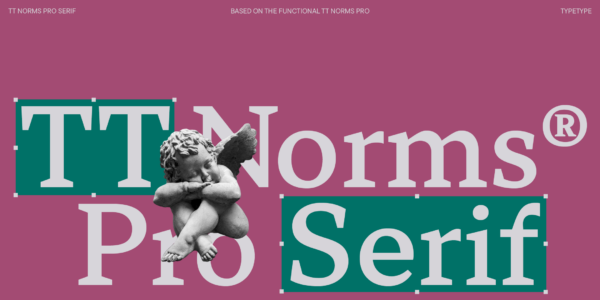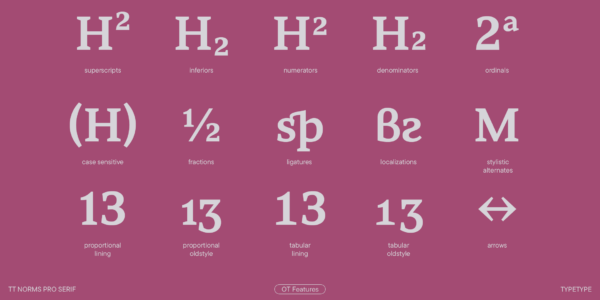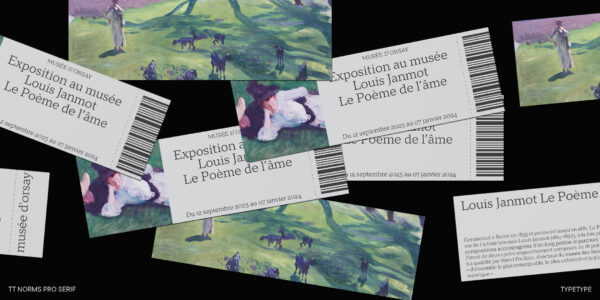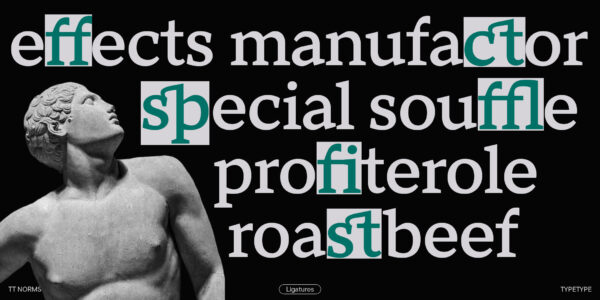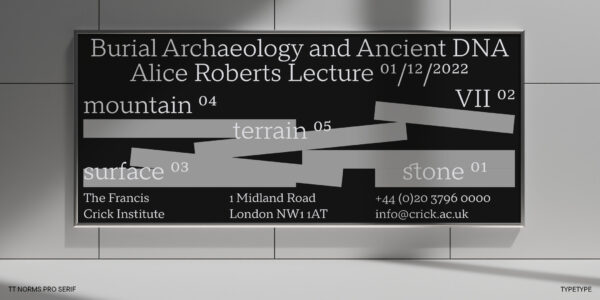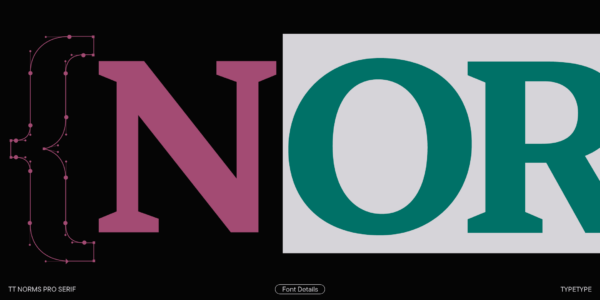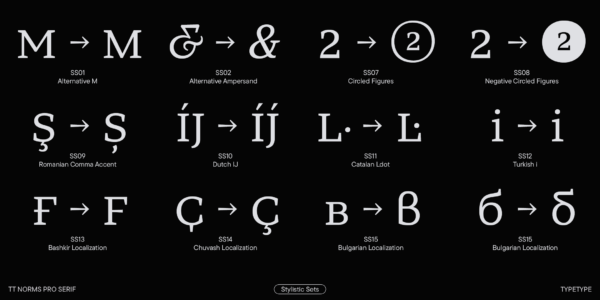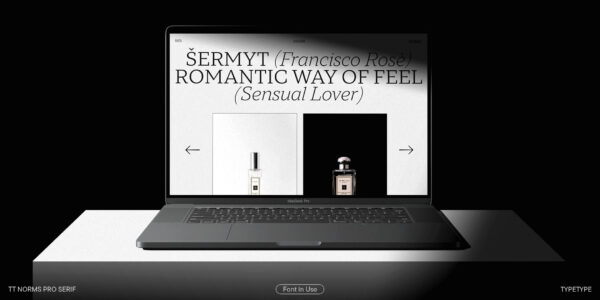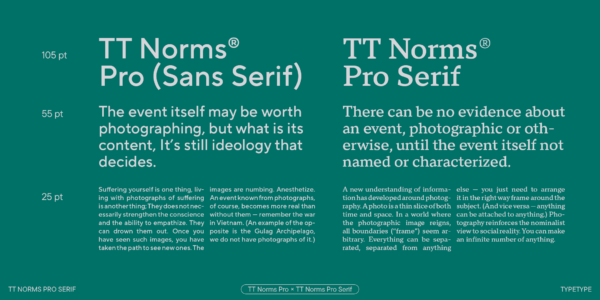
TT Norms® Pro Serif
TT Norms® Pro Serif — TT Нормс Про Сериф
«TT Norms» является зарегистрированным товарным знаком. «Pro» произносится как «про», и является разговорным сокращением слова профессиональный. «Serif» произносится как «сериф», в переводе с английского «антиква».
TT Norms® Pro Serif — функциональная и нейтральная, при этом элегантная антиква. Разработана на основе бестселлера TT Norms® Pro.
TT Norms Pro Serif — идеальная пара для главного гротеска от студии TypeType
В конце 2021 года мы задумали спроектировать антикву в пару к нашему бестселлеру TT Norms® Pro. Разработка шрифта заняла ровно один год. Данную антикву легко узнать по небольшому контрасту в пропорциях, наклону оси овалов, динамике ширин и контрасту в диагоналях. TT Norms Pro Serif — не просто дополнение, это полноценная антиква на базе функционального гротеска TT Norms® Pro. Наша новая антиква может использоваться на сайтах, для верстки книг, для оформления упаковок. В 2023 году мы провели большое обновление данного семейства, добавив несколько новых языков и опентайп фич.
1380 знаков, более 235 языков
Встречайте TT Norms® Pro Serif версии 1.100! Увеличили знаковый состав, добавили новые OpenType фичи и локализации для сербского и болгарского языков.
TT Norms® Pro Serif — функциональная антиква, разработанная на основе главного бестселлера студии — универсального гротеска TT Norms® Pro. Вместе они образуют идеальную шрифтовую пару. И хотя эти гарнитуры созданы друг для друга, они легко могут использоваться самостоятельно или составлять пару другим шрифтам.
Так, TT Norms® Pro Serif — самодостаточная, элегантная антиква, при этом вполне нейтральная. Ее легко узнать по лёгкой динамике в пропорциях, открытой апертуре, наклону оси овалов и небольшому контрасту штрихов. Другая характерная особенность этого шрифта — брутальные засечки, длина которых уменьшается пропорционально изменению жирности.
Как и в TT Norms Pro, здесь есть начертания Italic. Но для антиквы мы создали не просто наклонные начертания, а настоящие италики. Для них характерно изменение графем строчных знаков относительно прямых начертаний. Они становятся более округлыми, приближаясь к рукописным формам. Характер италика получился более резким, чем у прямых начертаний. В тексте c его помощью можно расставлять акценты, которые привлекут внимание, но не помешают чтению.
TT Norms® Pro Serif позволяет решить максимум дизайнерских задач. Шрифт обладает хорошей читаемостью, поэтому его можно применять даже в маленьких размерах. Область применения этой антиквы очень широка — ее можно использовать на сайтах, в печатной продукции, для оформления упаковок. Шрифт хорошо впишется в проекты, связанные с культурой и искусством, историей и литературой, подойдет для вывесок и афиш, дизайна элитных продуктов и услуг.
TT Norms® Pro Serif 1.100 — это:
• 24 начертания: 11 прямых, 11 наклонных и 2 вариативных шрифта, отдельные для прямых начертаний и италиков;
• 1380 глифов в каждом начертании.
• 31 OpenType фича, в том числе фичи локализации.
• Увеличили кассовый состав с 1236 до 1380 глифов, в частности — добавили знаки расширенной кириллицы, латиницы и знаки валют;
• Добавили две новых OpenType фичи — локализации для сербского и болгарского языков. Количество фич выросло с 29 до 31.
Basic Latin Basic Cyrillic Extended Latin Extended Cyrillic Currencies Vietnam Stylistic Alternates, Standard and Discretionary Ligatures|salt,liga,dlig,frac Punctuation, Symbols, Mathematical Symbols, Arrows Figures in circles
ss01 | Alternative M
M
ss02 | Alternative Ampersand
&
ss07 | Circled Figures
1 2 3
ss08 | Negative Circled Numbers
0 1 2
ss09 | Romanian Comma Accent
Şş Ţţ